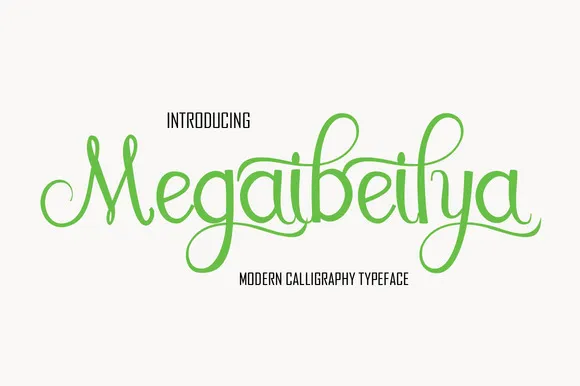
Megaibeilya Script Font – Download Grátis
A Megaibeilya Script Font é uma delicada criação para designers que desejam adicionar um toque autêntico ao seu trabalho com letras de calligrafia. Seu design fluido e elegante se ajusta perfeitamente a textos grandes e pequenos, permitindo assim tanto uma utilização em projetos publicitários quanto em trabalhos editoriais. Com traços leves e detalhes meticulosamente executados, essa fonte traz o charme da calligrafia à sua página de download, oferecendo um olhar especial que certamente deixará seu projeto destaco no arco das suas criações digitais. Ideal para quem aprecia a sofisticação e a precisão do design gráfico, a Megaibeilya Script é uma opção inegável para aqueles buscam trazer uma cor poética à sua marca visual.